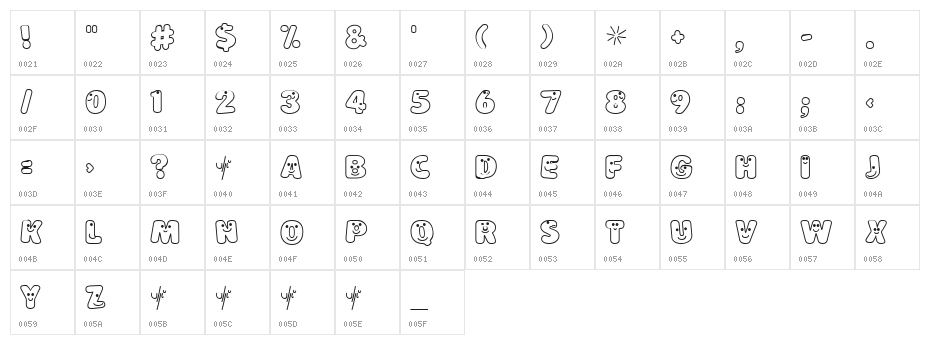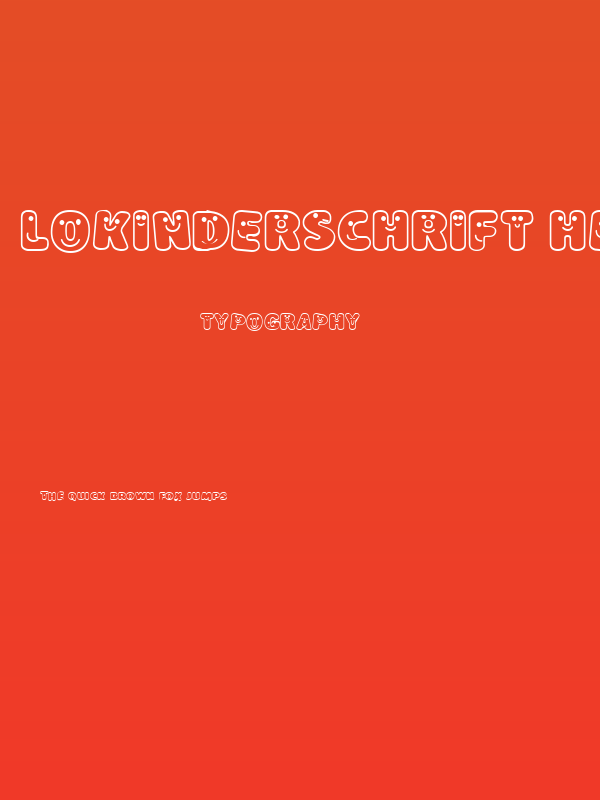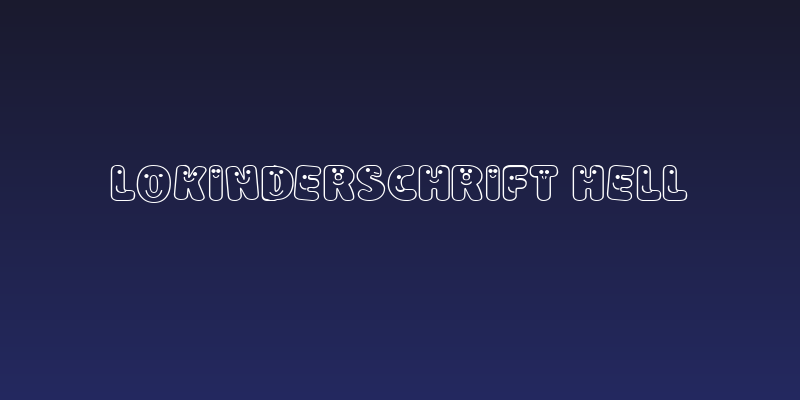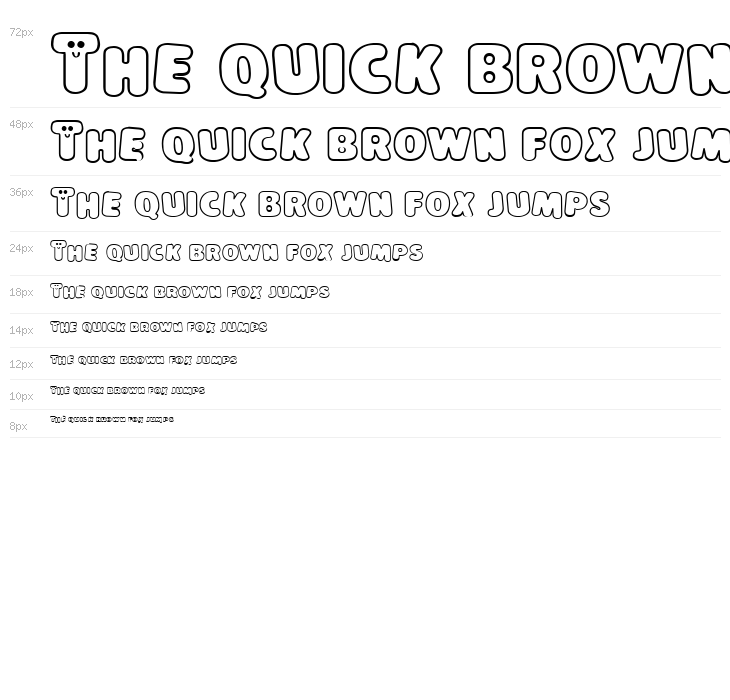
LoKinderSchrift Hell Font
| 名称 | LoKinderSchrift Hell |
| 重量 | Hell |
| 分类 | Cartoon |
| 整体风格 | Playful, Whimsical |
| 使用场景 | Headlines, Logos, Children's materials |
| 推荐项目 | Ideal for children's books, educational materials, playful branding, and party invitations. |